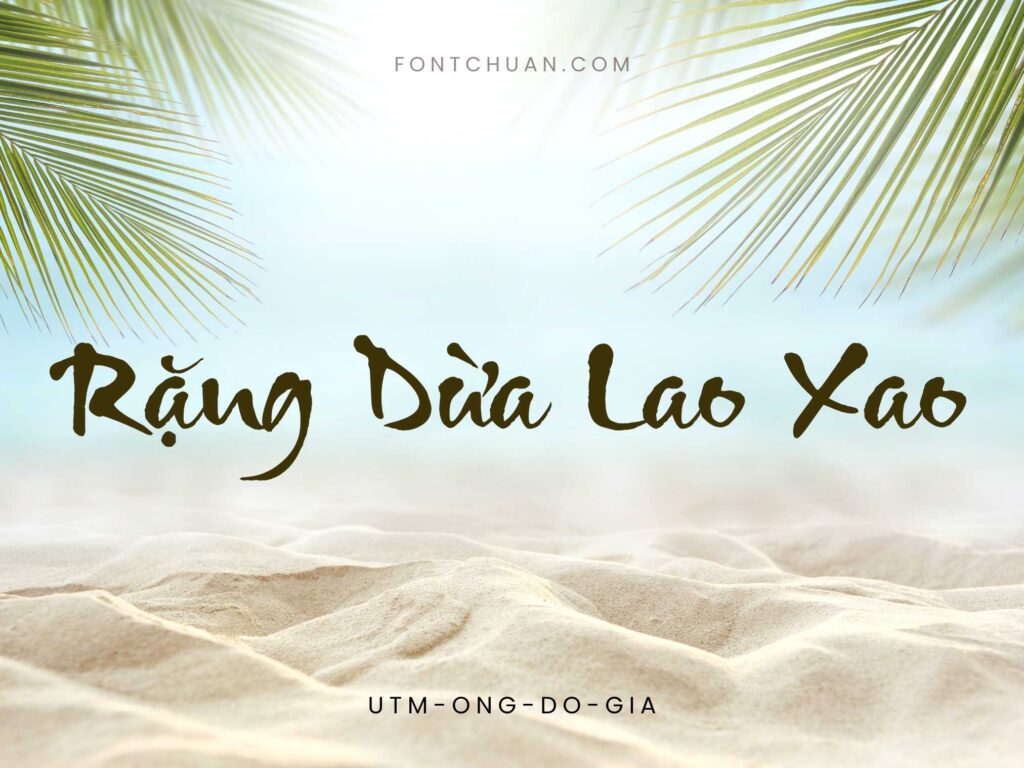
Font UTM Ông Đồ Già Việt Hóa
UTM Ông Đồ Già là một font chữ mang phong cách Font chữ thư pháp truyền thống, tái hiện nét chữ viết tay đầy nghệ thuật của các ông đồ xưa. Đồng thời, font này cũng mang hơi hướng Font cổ trang, gợi nhắc đến những bức thư pháp cổ và văn bản xưa, tạo cảm giác hoài cổ và trang trọng. Font này thường xuất hiện trong các dịp lễ hội, ngày Tết và các sự kiện mang tính văn hóa. Font đã được Việt hóa để hỗ trợ tiếng Việt, giúp mở rộng khả năng ứng dụng trong nhiều lĩnh vực thiết kế. Thành viên của Font Chuẩn đã sưu tầm và giới thiệu font này nhằm đáp ứng nhu cầu bạn đọc, cung cấp nguồn tham khảo chất lượng và ứng dụng thực tế vào các dự án thiết kế.
Về đặc điểm thiết kế, UTM Ông Đồ Già sở hữu những đường nét uốn lượn mềm mại, độ tương phản cao và nét chữ thư pháp đậm chất Á Đông. Font này phù hợp với nhiều ứng dụng như thiết kế poster, thiệp chúc mừng, biển hiệu, banner và các ấn phẩm mang tính văn hóa truyền thống. Các ngành nghề như quảng cáo, ẩm thực, thiệp cưới và giáo dục có thể tận dụng font này để tạo nên sự khác biệt và thu hút trong các sản phẩm thiết kế